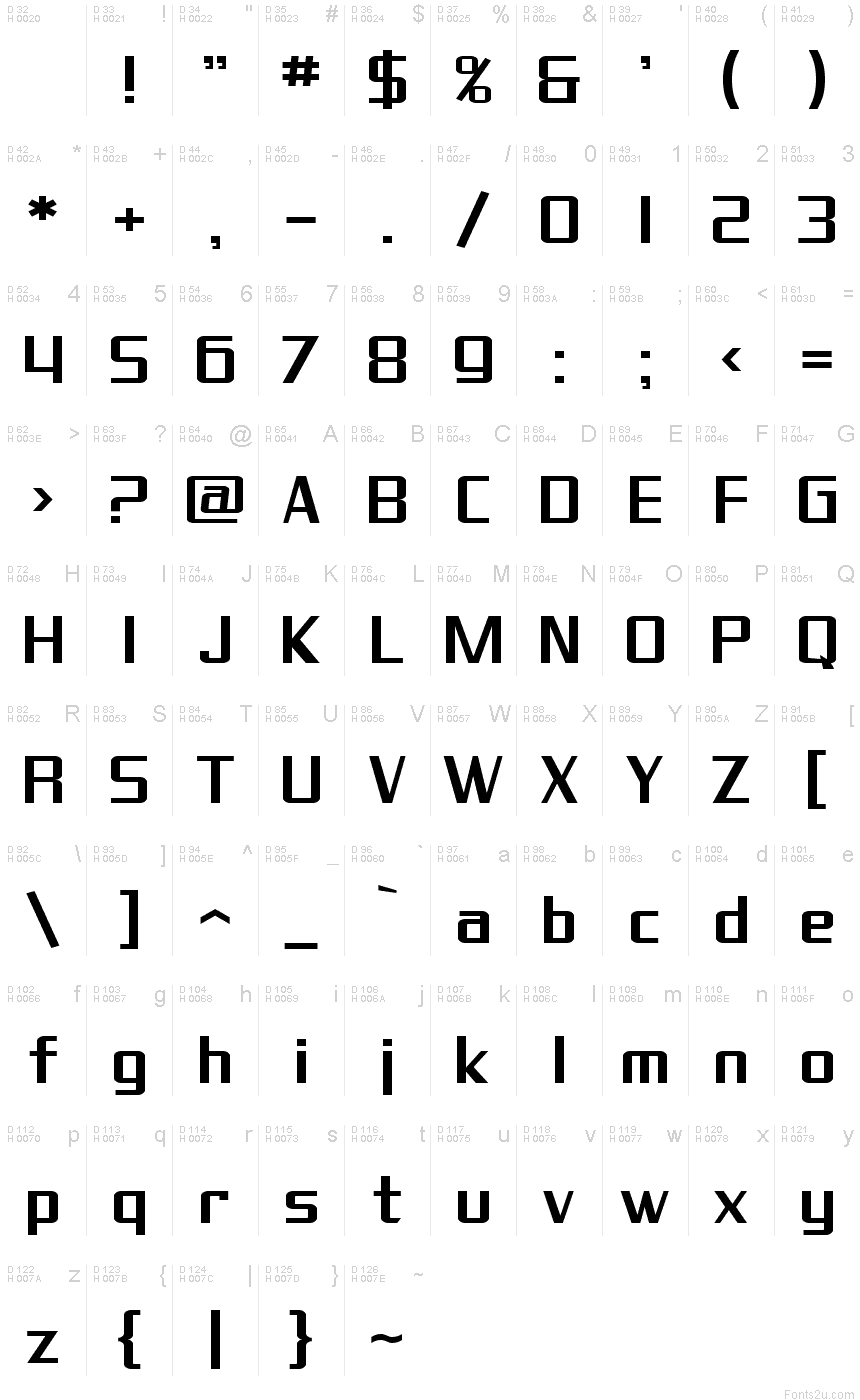
SF Theramin Gothic di ShyFonts Type Foundry è un font display techno gratuito con le tipiche sonorità elettroniche della fine degli anni '90. Le lettere sono costruite su curve quadrate e angoli retti netti, conferendo all'alfabeto un ritmo modulare e scandito, a metà strada tra la segnaletica e l'interfaccia di un sintetizzatore, con il giusto peso gotico nelle linee verticali per donare stabilità.
È ideale per titoli di locandine, loghi di videogiochi, flyer da club, copertine di album e branding orientato agli schermi, dove serve un font gratuito che trasmetta un'estetica più "wired" che levigata. Poiché le forme si incastrano alla perfezione, SF Theramin Gothic è perfetto per titoli brevi, schermate di presentazione e monogrammi che richiedono una presenza compatta e un look tagliato a macchina.